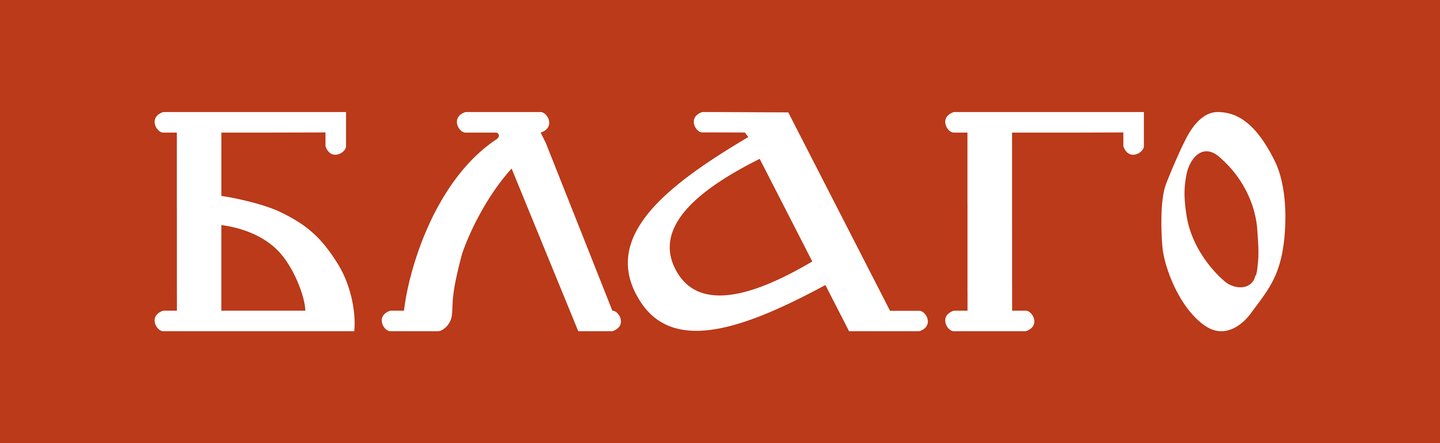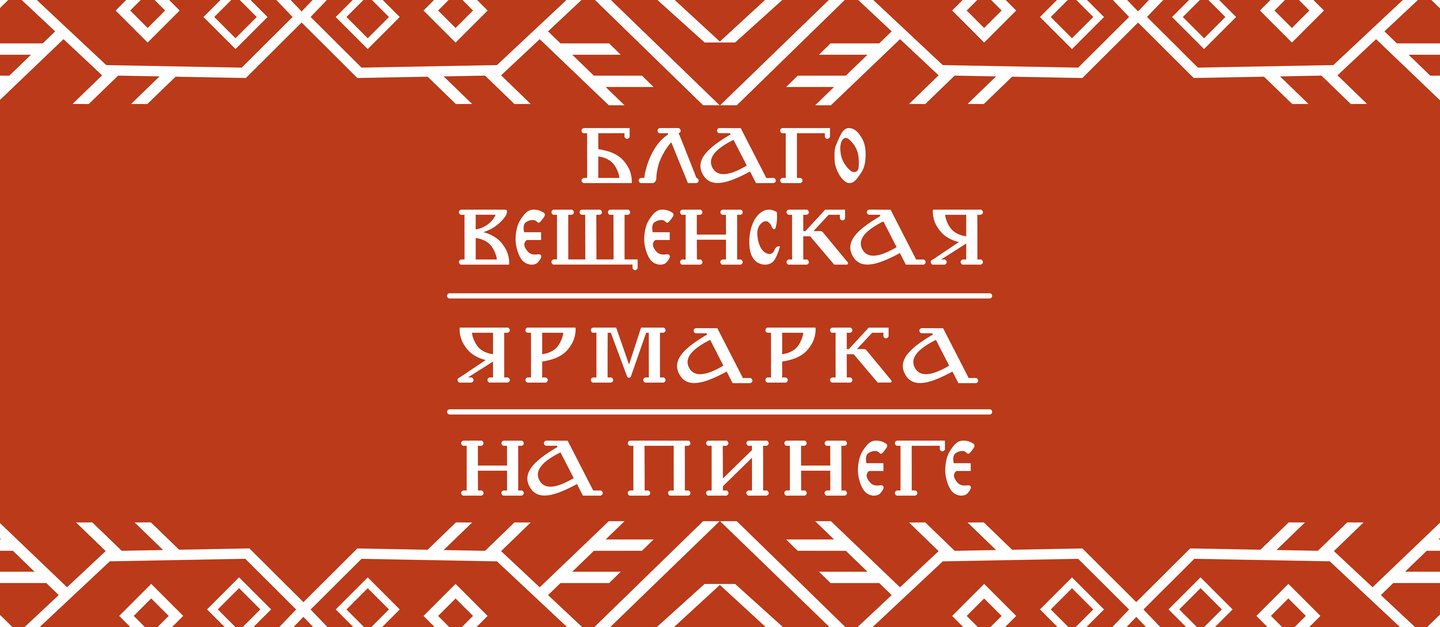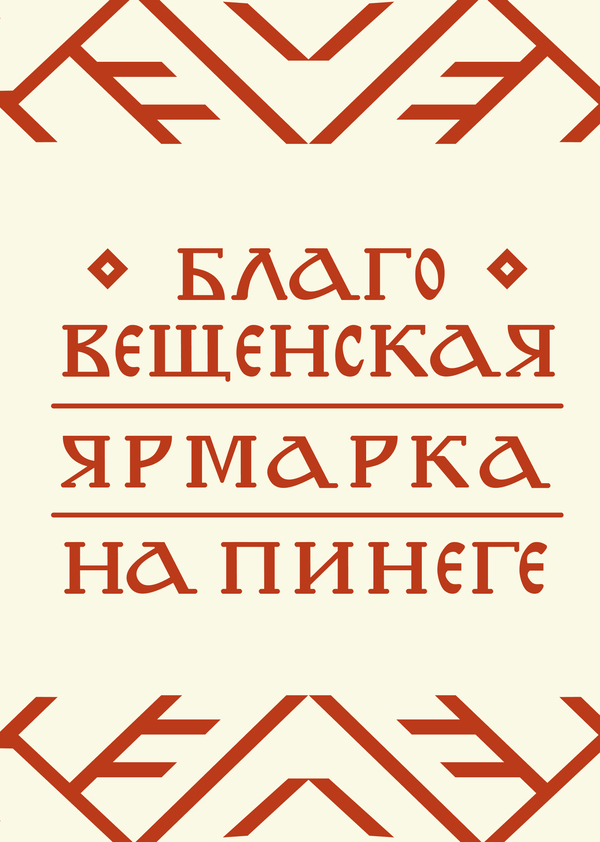
Пинежье: код ярмарки
С 9 до 16 марта прошла экспедиция на Пинегу. Задачей блока дизайна была разработка обновлённой визуальной айдентики и коммуникации для XI Благовещенской Ярмарки. Под кураторством Алексии Ерёминой мною был разработан шрифт «Благо».
Шрифт является основной типографической составляющей обновлённого логотипа ярмарки, а также используется как акцидентный в фирменном стиле на других носителях.